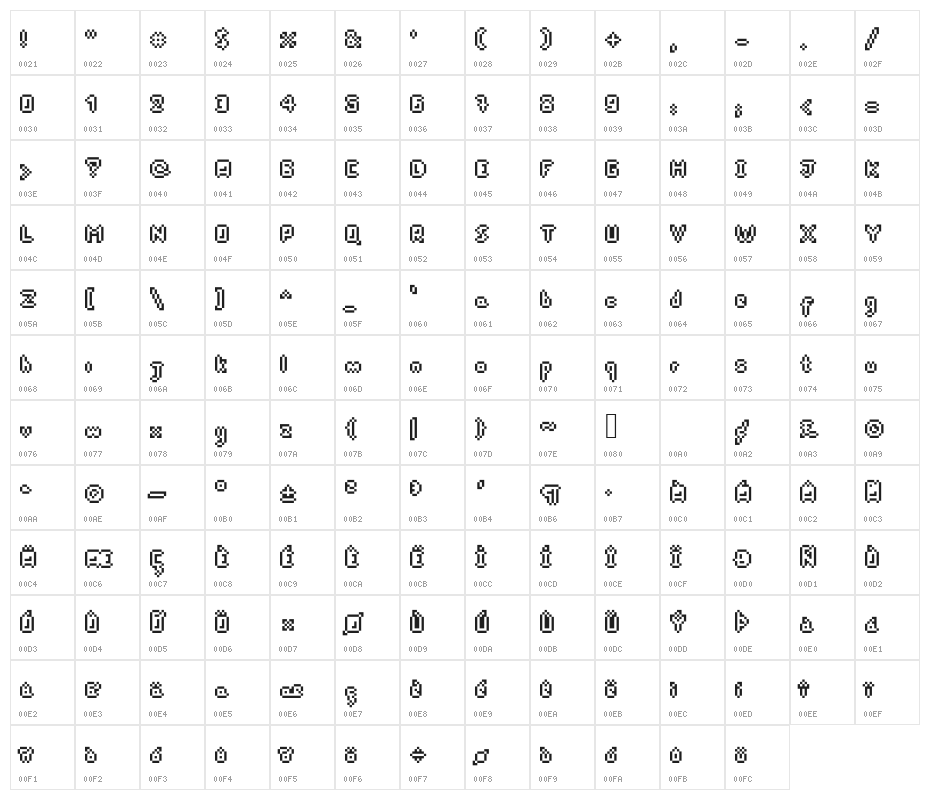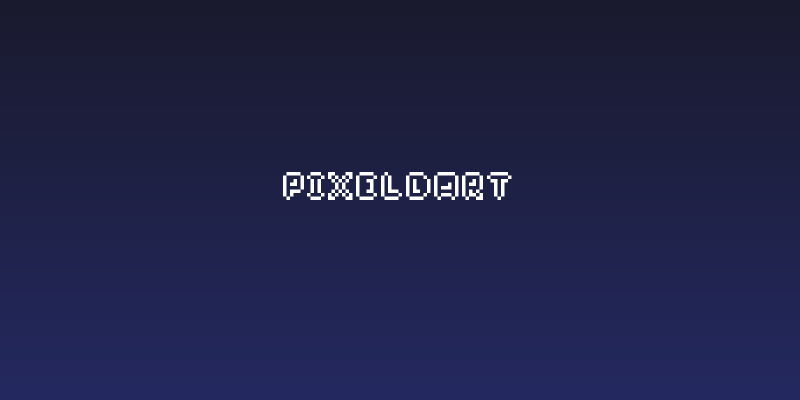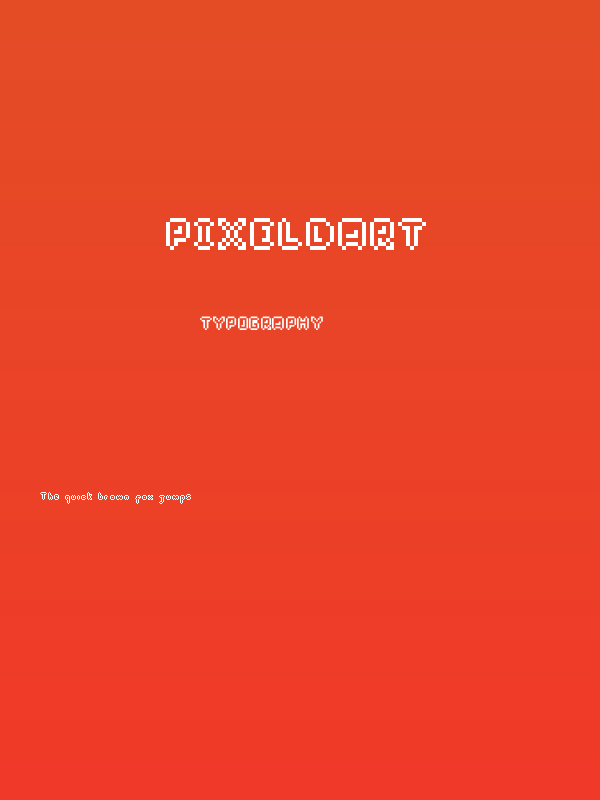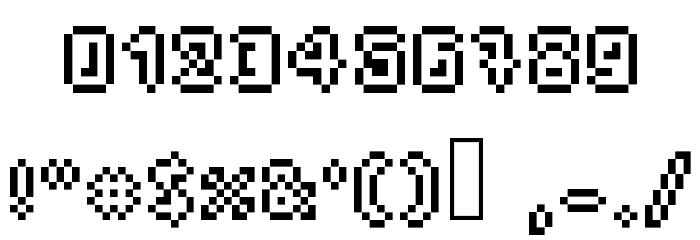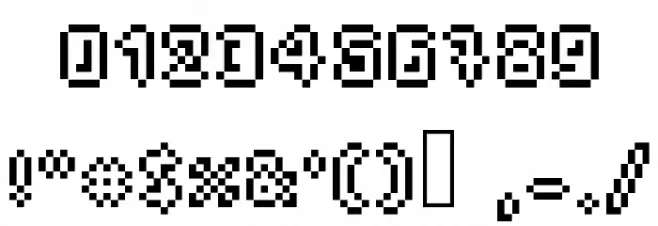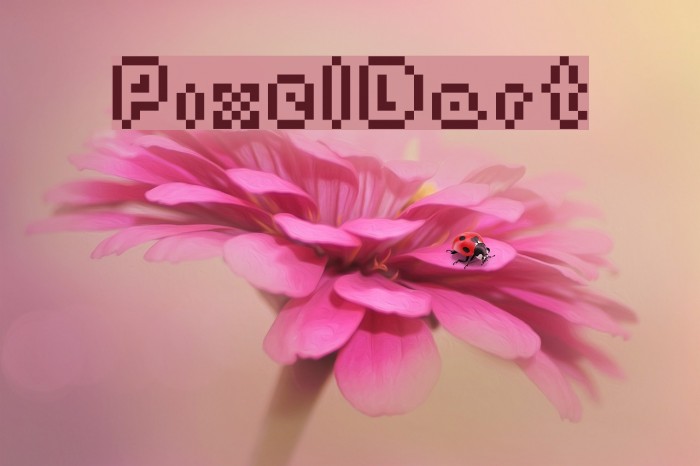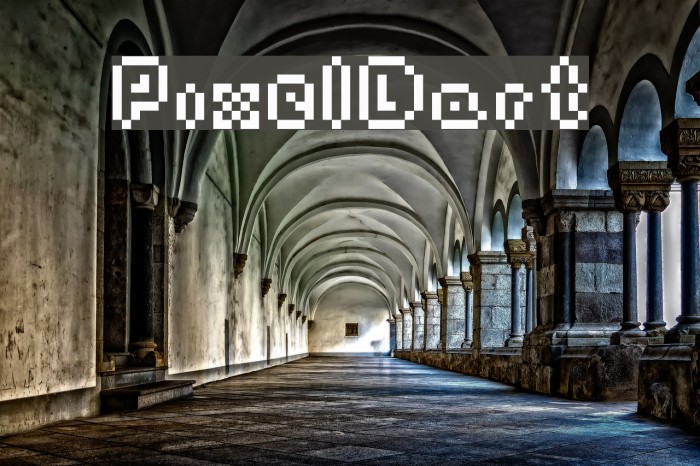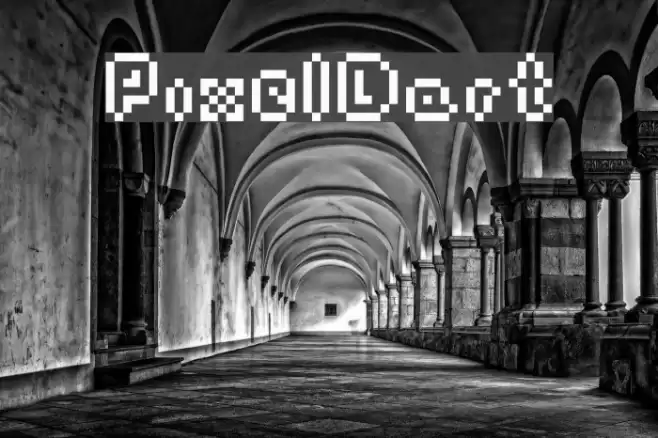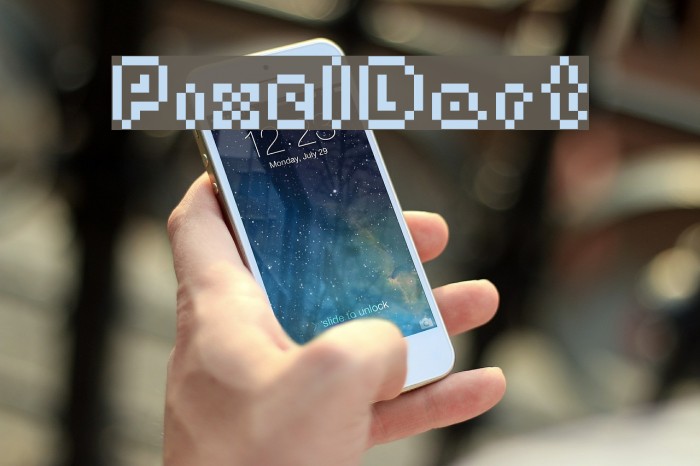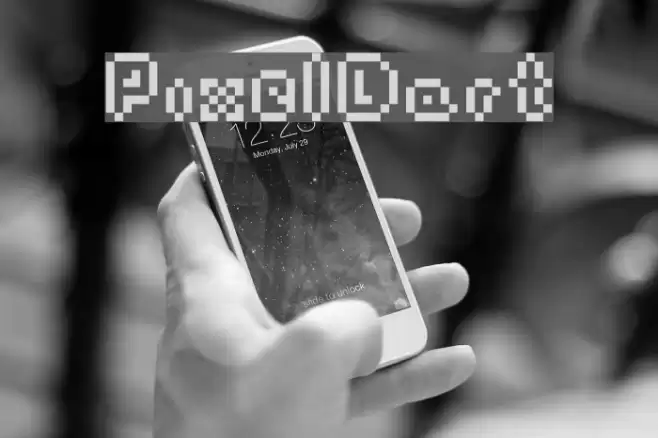
PixelDart Font
| Gesamtstil | Vintage |
| Anwendungsfall | Logos, Headlines, Digital Art |
| Vorgeschlagene Projekte | Ideal for video game graphics, retro-themed posters, digital art projects, and any design requiring a vintage digital look. |